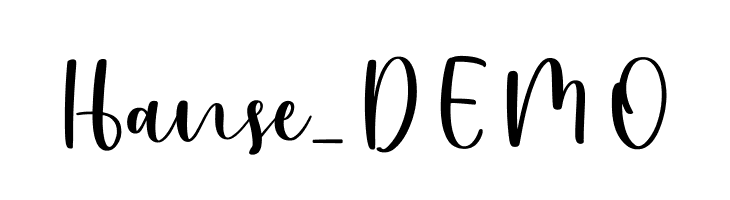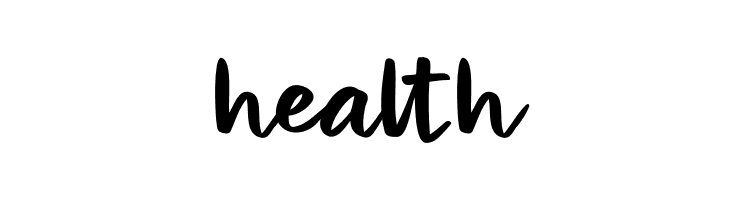
( Fonts by Des Gomez )
A playful, hand-drawn font with bold, whimsical characters.
A handwritten, playful font with elongated, narrow strokes and a casual flair.
A playful, handwritten font with a casual and friendly style.
A whimsical, hand-drawn font with playful, uneven strokes and a dynamic feel.
A dynamic, handwritten font with an oblique, energetic style.
A bold, geometric font with sharp angles and a futuristic style.
( Fonts by Des Gomez )
A playful, hand-drawn font with tall, narrow characters and a whimsical style.
A dynamic script font with a fluid, handwritten style.
A regal, medieval-inspired font with intricate flourishes and decorative elements.
A playful, hand-drawn outline font with a whimsical and cartoonish style.
( Fonts by Maelle.K - Thomas Boucherie )
A dynamic, slanted handwritten font with fluid, connected letters.
A playful, rounded, handwritten-style font with smooth curves.
A hand-drawn, casual font with a playful, handwritten style.
A playful, handwritten font with a casual and organic feel.